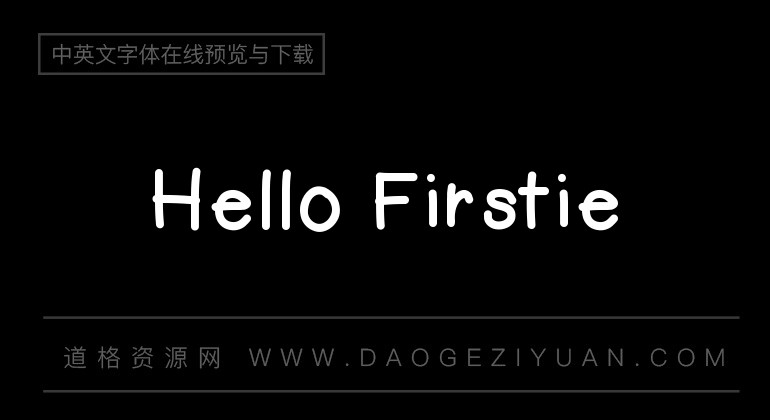
Hello Firstie是一款简洁、清新、可爱的手写字体,由著名的设计师Brianna Gorton设计。它具有自然、可爱的外观,更加温柔、柔和,能够满足您的设计需求。它的字体曲线流畅,笔画细腻,给人一种清新抒情的感觉,能够更好地表达您的情感。它还具有多种字体风格,可以满足您的不同需求,是一款非常适合创作漂亮文字设计的字体。内容介绍
Hello Firstie是一款非常不错的手写艺术字体,具有很好的视觉感,适合于文化类的宣传设计、商业类品牌的广告和产品包装设计以及个性化文字排版等较多场景。